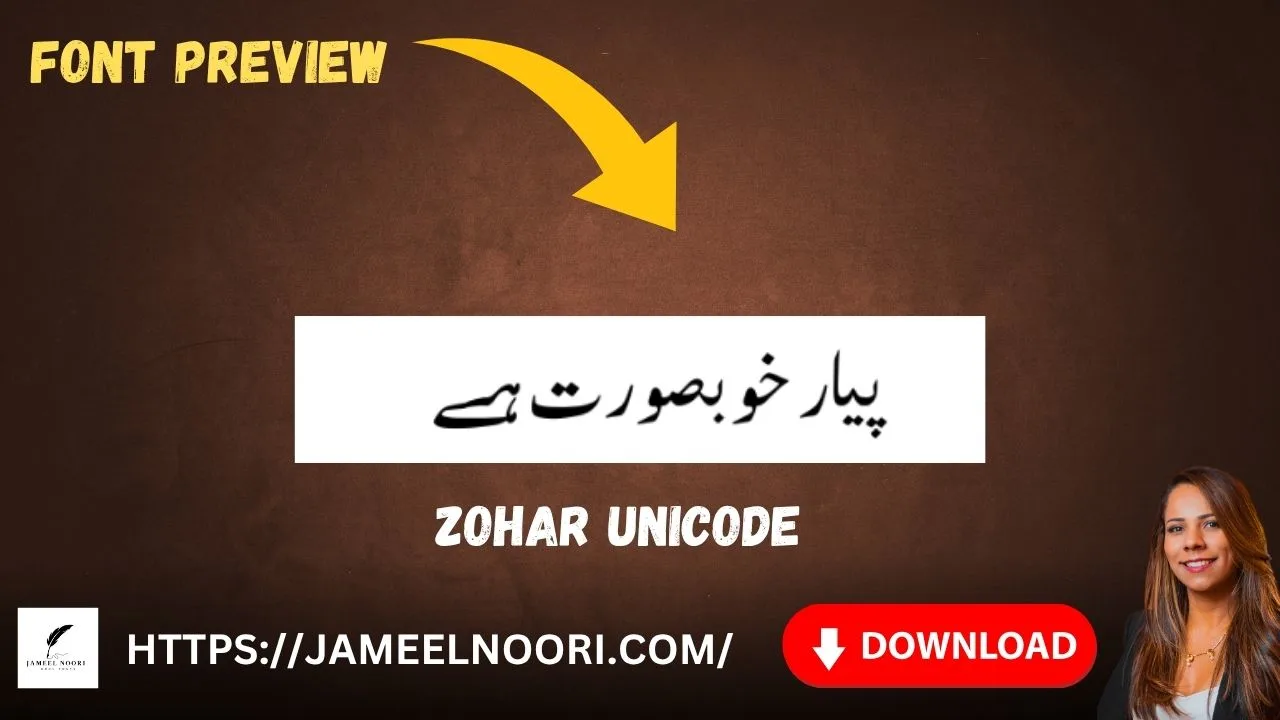
Zohra Unicode Font aik mashhoor aur elegant Urdu TrueType font hai jo Urdu likhne walon ke liye perfect choice mana jata hai. Ye font un users ke liye design kiya gaya hai jo apne documents, posters aur digital designs me clear aur readable Urdu typing chahte hain.
What is Zohra Unicode Font?
Zohra Unicode Font aik free Urdu TrueType font hai jo Windows aur Mac dono systems par smoothly kaam karta hai. Ye font Unicode-based hai, iska matlab ye hai ke ye har Urdu character aur symbol ko accurate display karta hai.
Is font ka design bohot stylish aur professional lagta hai, jo aapke Urdu content ko elegant aur modern touch deta hai.
Key Features:
- Unicode Supported Urdu Font
- Lightweight aur fast rendering
- Clear aur easy-to-read design
Why Choose Zohra Unicode Font for Urdu Typing?
Agar aap professional Urdu writing, designing ya publishing ka kaam karte hain to Zohra Unicode Font ek perfect Urdu font hai. Is font ka TrueType structure ensure karta hai ke har letter smooth aur balance me nazar aye.
Ye font especially un logon ke liye best hai jo stylish fonts dhoond rahe hain lekin readability ko compromise nahi karna chahte.
Reasons to Choose:
- Stylish yet Traditional Urdu Look
- Perfect for both Print & Digital Media
Best Uses of Zohra Unicode Urdu Font
Zohra Unicode Font ko aap multiple purposes ke liye use kar sakte hain. Ye font readability aur style dono ka perfect balance rakhta hai.
Best Uses Include:
- Urdu documents aur letters typing
- Graphic design projects
- Social media posts aur quotes
- Websites aur Urdu blogs
Agar aap Urdu typing aur design ke liye ek elegant, lightweight aur Unicode-supported font chahte hain to Zohra Unicode Font aapka best choice hai. Ye font har Urdu writer aur designer ke liye perfect tool hai jo apne work ko next level tak le jana chahta hai.
What is Zohra Unicode Font?
Zohra Unicode Font is a TrueType Urdu font designed for clear and stylish Urdu writing.
Does Zohra Unicode Urdu Font support Unicode characters?
Yes, it supports all Urdu Unicode characters perfectly.